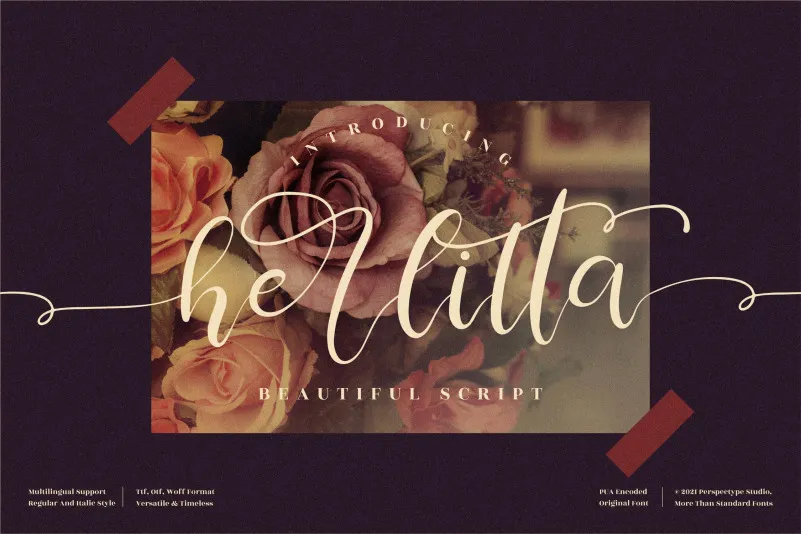
A ‘Herlitta Font’ é uma elegante tipografia script que traz aos designers um estilo sofisticado e moderno. Suas linhas delicadas e sua aparência refinada tornam-na perfeita para criações de marca, convites de casamento, estilos de papel ou até mesmo postagens nas redes sociais. Seu uso versátil permite que você personalize desde a identidade visual do seu negócio até os mais detalhados elementos de um evento especial. Um dos seus principais benefícios é o fato de ser PUA (Portable User Area) codificada, permitindo acesso fácil a todos os sinais e desenhos alternativos sem precisar de ferramentas adicionais. A ‘Herlitta Font’ oferece aos criadores um amplo leque para expressarem suas ideias em um formato que se adequa perfeitamente à linguagem visual contemporânea.